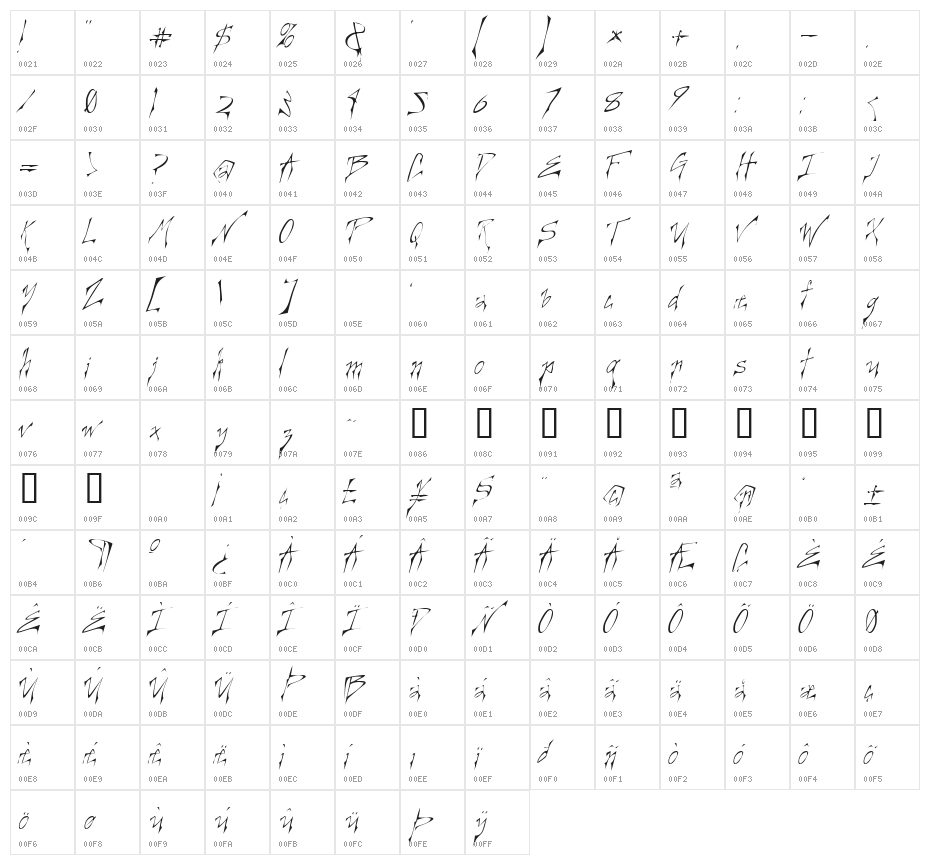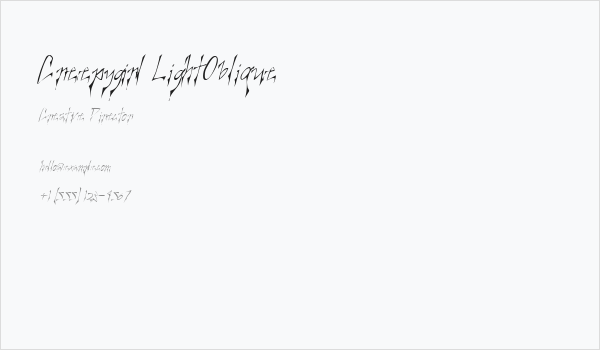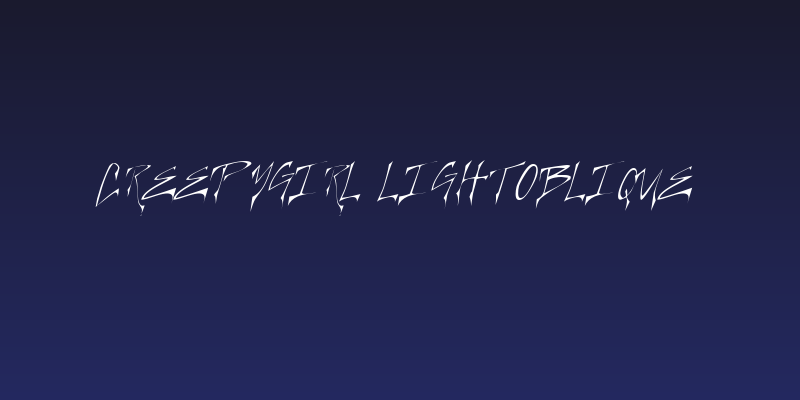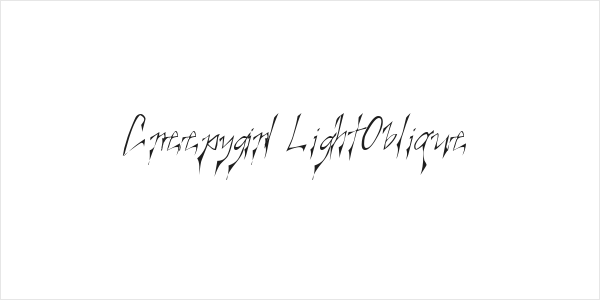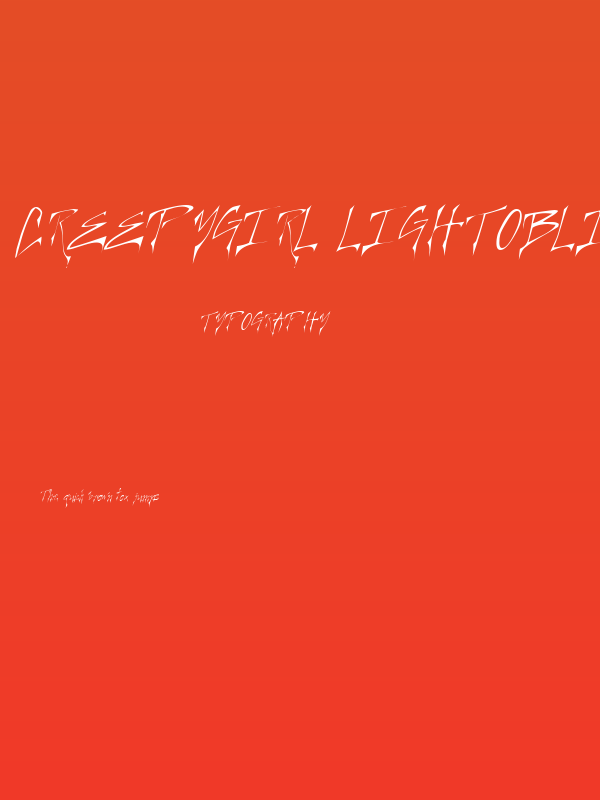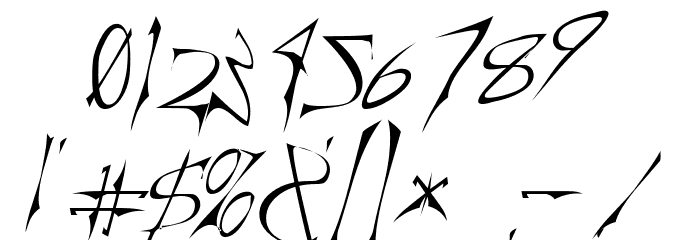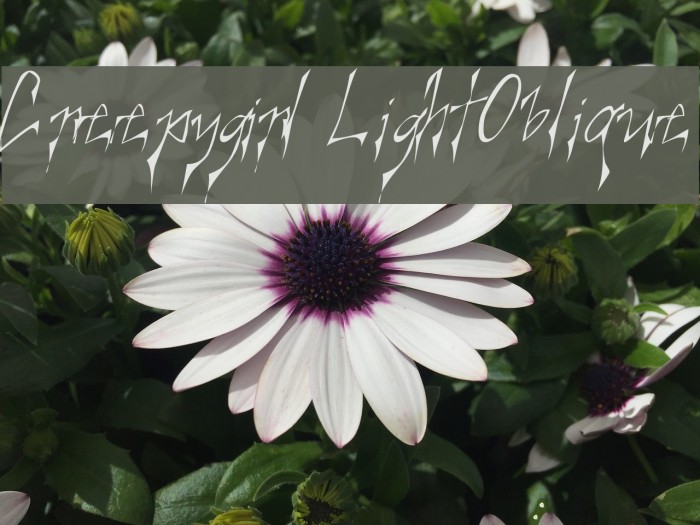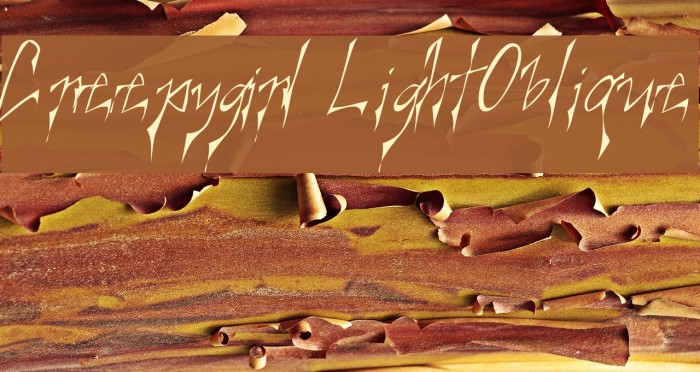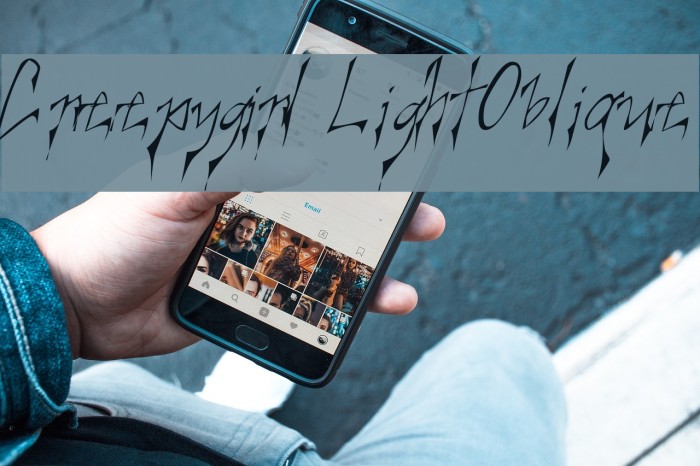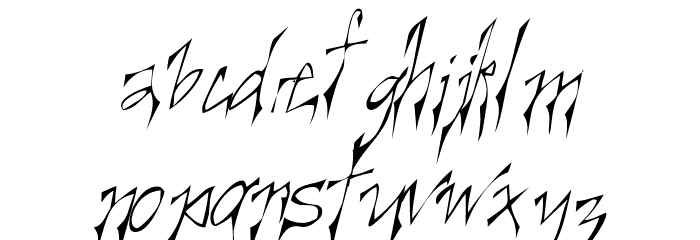
Creepygirl LightOblique Font
| Vorgeschlagene Projekte | Ideal for horror-themed posters, Halloween invitations, or any project requiring a dramatic, eye-catching typeface. |